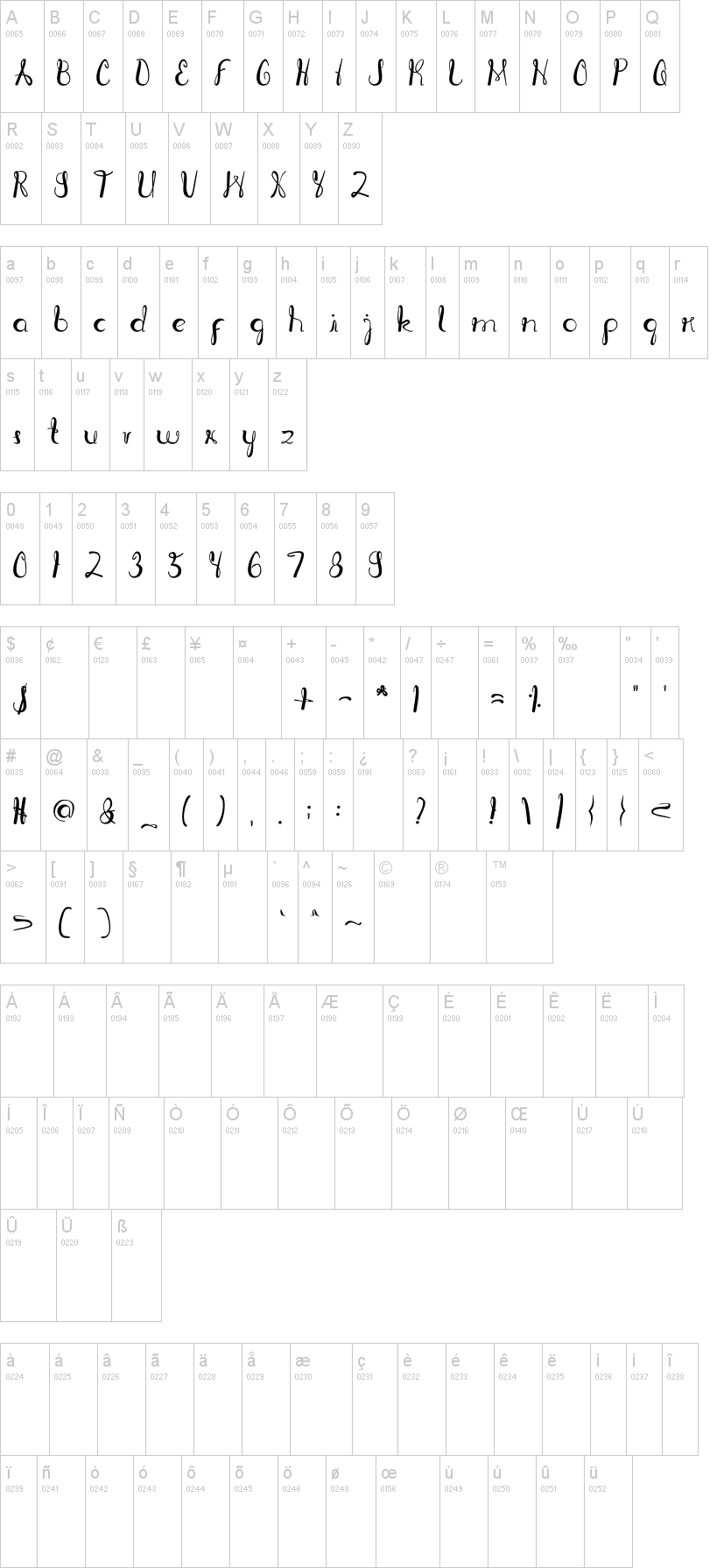
Ragatnia Clara
Ragatnia Clara 是一款非常受欢迎的英文字体,它具有细腻而优雅的外观,且易于阅读。它是一种粗体字体,具有明显的粗细变化,使字体看起来更加生动有趣。Ragatnia Clara 字体的字母与数字具有较大的差异,使它们更容易被识别。它的笔画细腻,曲线优美,使文字具有柔和的感觉。此外,Ragatnia Clara 字体具有良好的可读性,适用于多种不同风格的设计,例如海报、书籍、海报等。
Ragatnia Clara是一款非常不错的手写艺术字体,具有很好的视觉感,适合于文化类的宣传设计、商业类品牌的广告和产品包装设计以及个性化文字排版等较多场景。